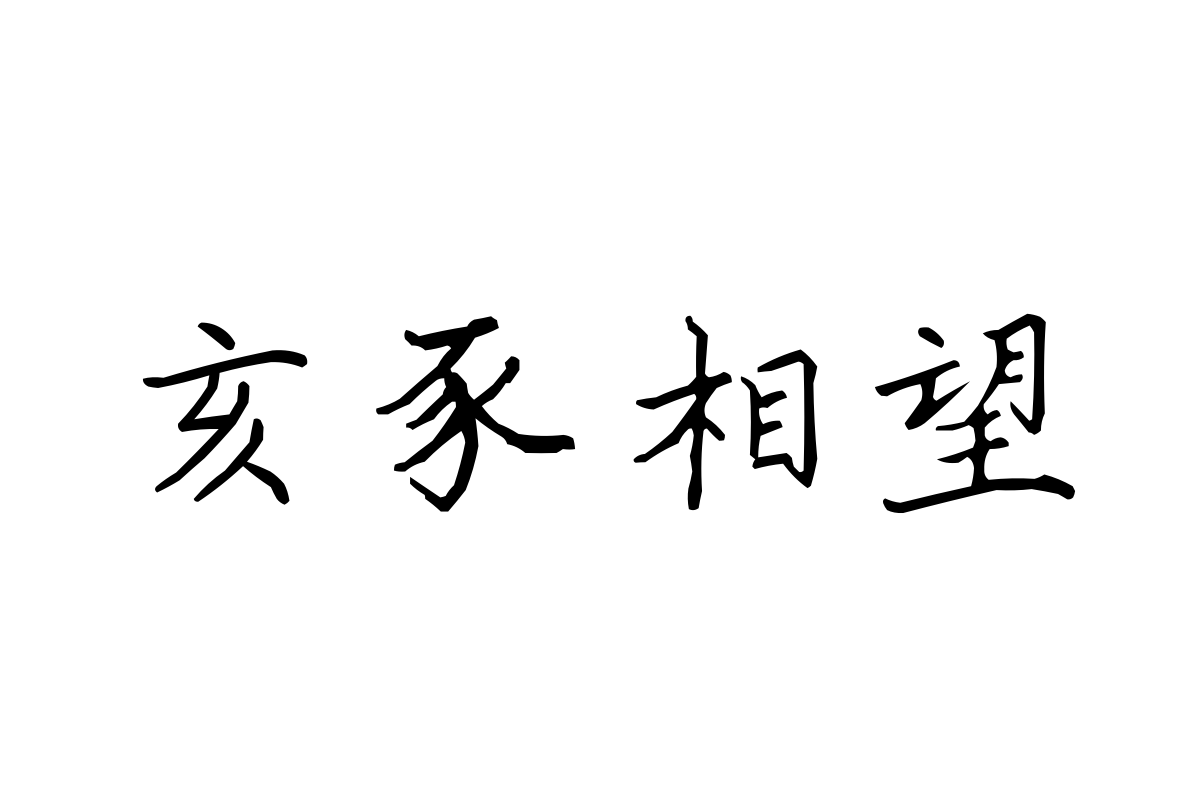
三极文明楷书字体是一种具有深厚文化底蕴的书法字体,它源自中国古代的楷书艺术。这种字体的特点是笔画流畅、结构严谨、形态优美,具有很强的艺术感和美感。
在三极文明楷书字体中,每个笔画都经过精心设计和雕琢,形成了独特的风格。这种字体的笔画粗细适中,既有力度又有美感,使得整个字体看起来既庄重又不失灵动。
此外,三极文明楷书字体还注重字与字之间的空间关系,使得整个字体看起来既紧凑又富有层次感。这种字体的布局非常讲究,每一个字都恰到好处地与其他字相呼应,形成了一种和谐的整体效果。
总的来说,三极文明楷书字体是一种具有很高艺术价值和审美价值的书法字体,它不仅能够展现出书写者的文化素养和艺术修养,也能够给观者带来美的享受和心灵的震撼。